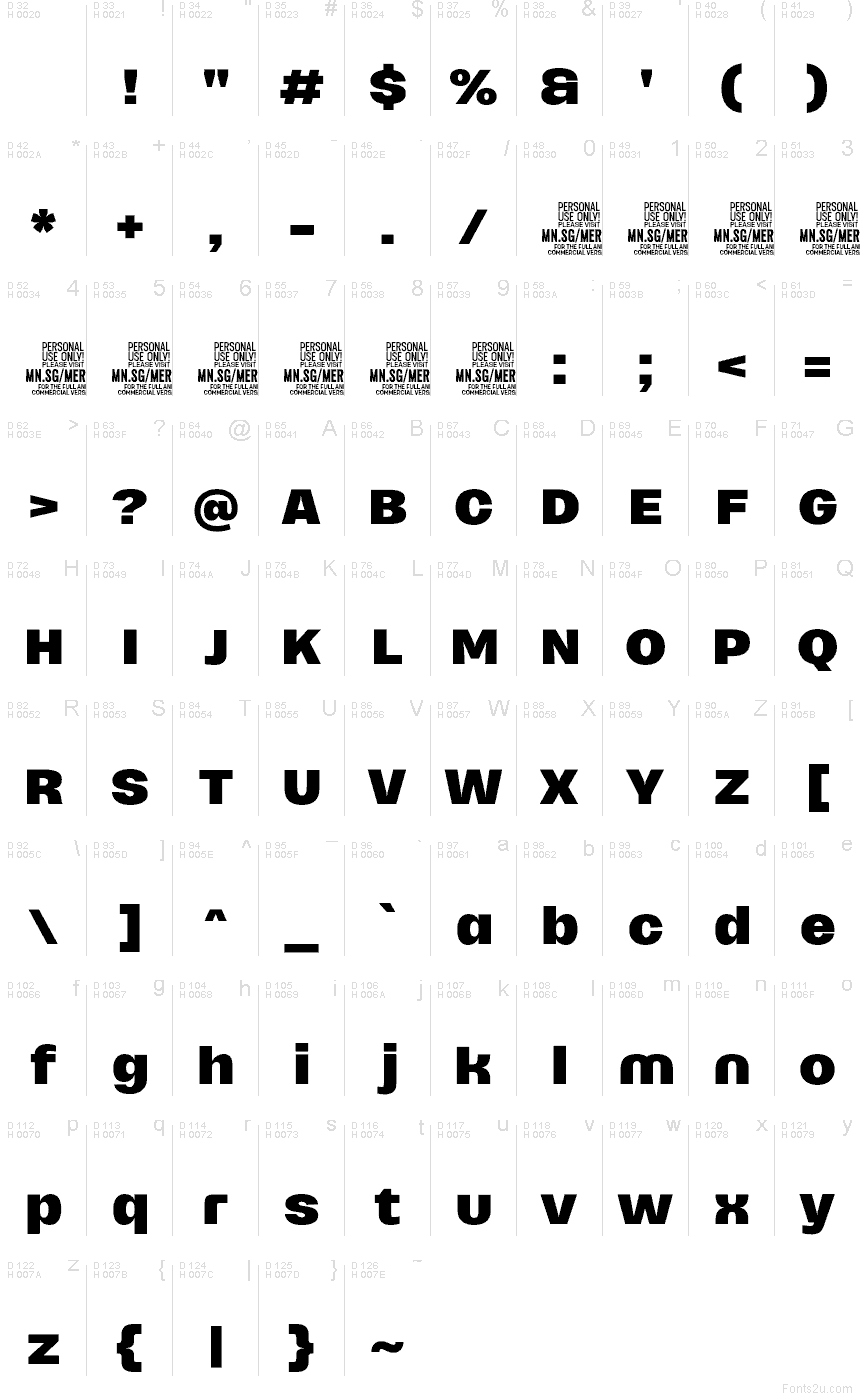
Merica Futurist PERSONAL USE Bold
Merica Futurist von Mans Greback AB ist eine kostenlose, futuristische serifenlose Schrift mit einem kräftigen, abgerundeten Aufbau und einer cleanen Retro-Tech-Anmutung. Die Buchstaben wirken zugleich breit und kompakt, während die weichen Ecken und stumpfen Abschlüsse dem Alphabet einen soliden, fast modularen Rhythmus verleihen.
Diese kostenlose Schriftart eignet sich hervorragend für das Branding von Gaming- oder Tech-Projekten, Plakatüberschriften, Albumcover, Titelkarten und Verpackungsdesigns, bei denen Sie eine kühne, synthetische Aussagekraft suchen, ohne dabei in reine Sci-Fi-Klischees zu verfallen. Sie passt auch perfekt zu kurzen Logos und App-Schriftzügen, da die schweren Formen und die abgerundete Geometrie selbst in engen Layouts eine freundliche Wirkung erzielen.